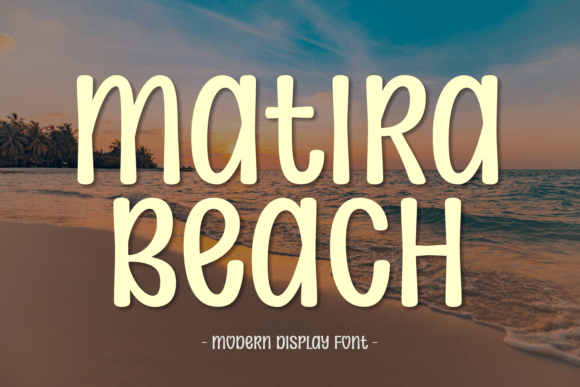
Matira Beach
找到合适的设计元素可能具有挑战性,但 Matira Beach 提供了一系列出色的藏品,可瞬间提升您的作品质量。
精心制作的 Matira Beach 提供干净的矢量、流畅的排版以及让您安心的商业许可证。
无论您是创建 POD(按需打印)产品、婚礼邀请函还是社交媒体图形,Matira Beach 都是理想的选择。